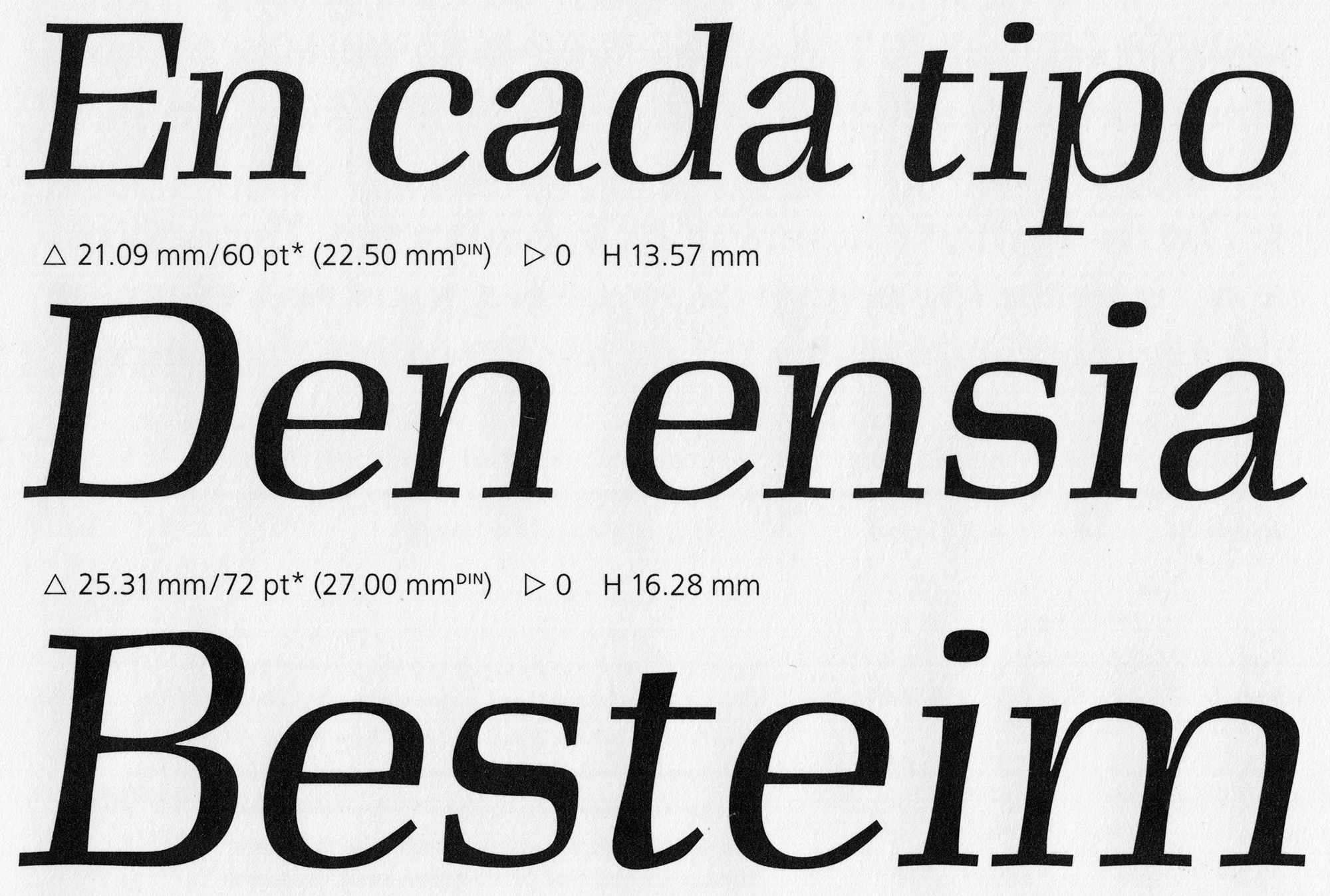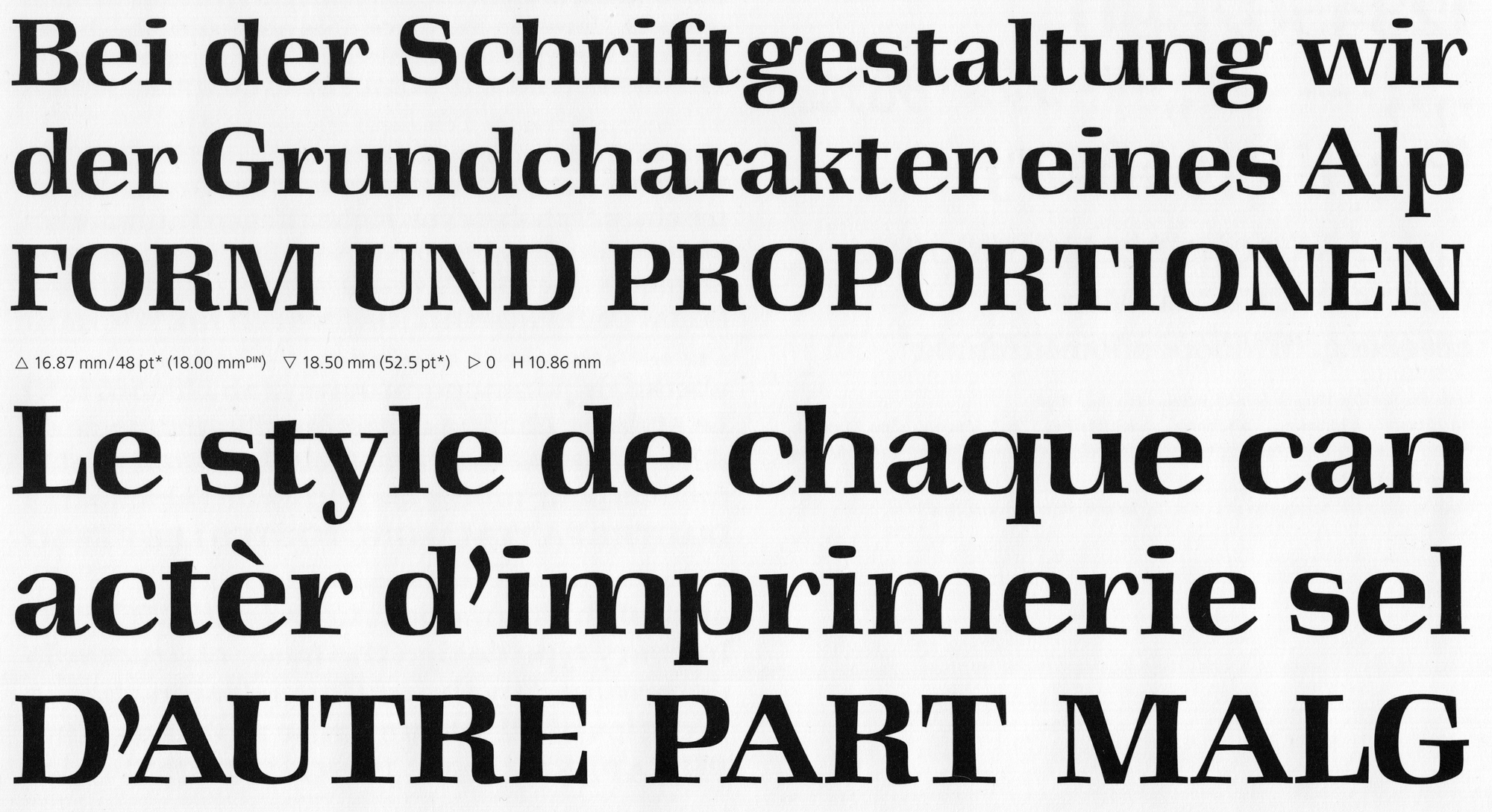
- circa 1966
- Antiqua humanistisch
Die Antikva Margaret ist eine charakterstarke Antiqua des ungarischen Designers Zoltán Nagy. Der Entwurf wurde bei einem Schriftgestaltungswettbewerb der Visual Graphics Corporation eingereicht und zählte zu den Gewinnern. Die Schrift wurde bis in die 1970er-Jahre weiter ausgebaute und verfügte schlussendlich über vier Strichstärken (light bis black) und einen kursiven Schnitt. Die Schnitte waren über verschiedene Fotosatzanbieter und als Abreibebuchstaben verfügbar.
Die Olde Megrat NF von Nick’s Fonts basiert auf der Antikva Margaret, verfügt aber lediglich über einen Schnitt.